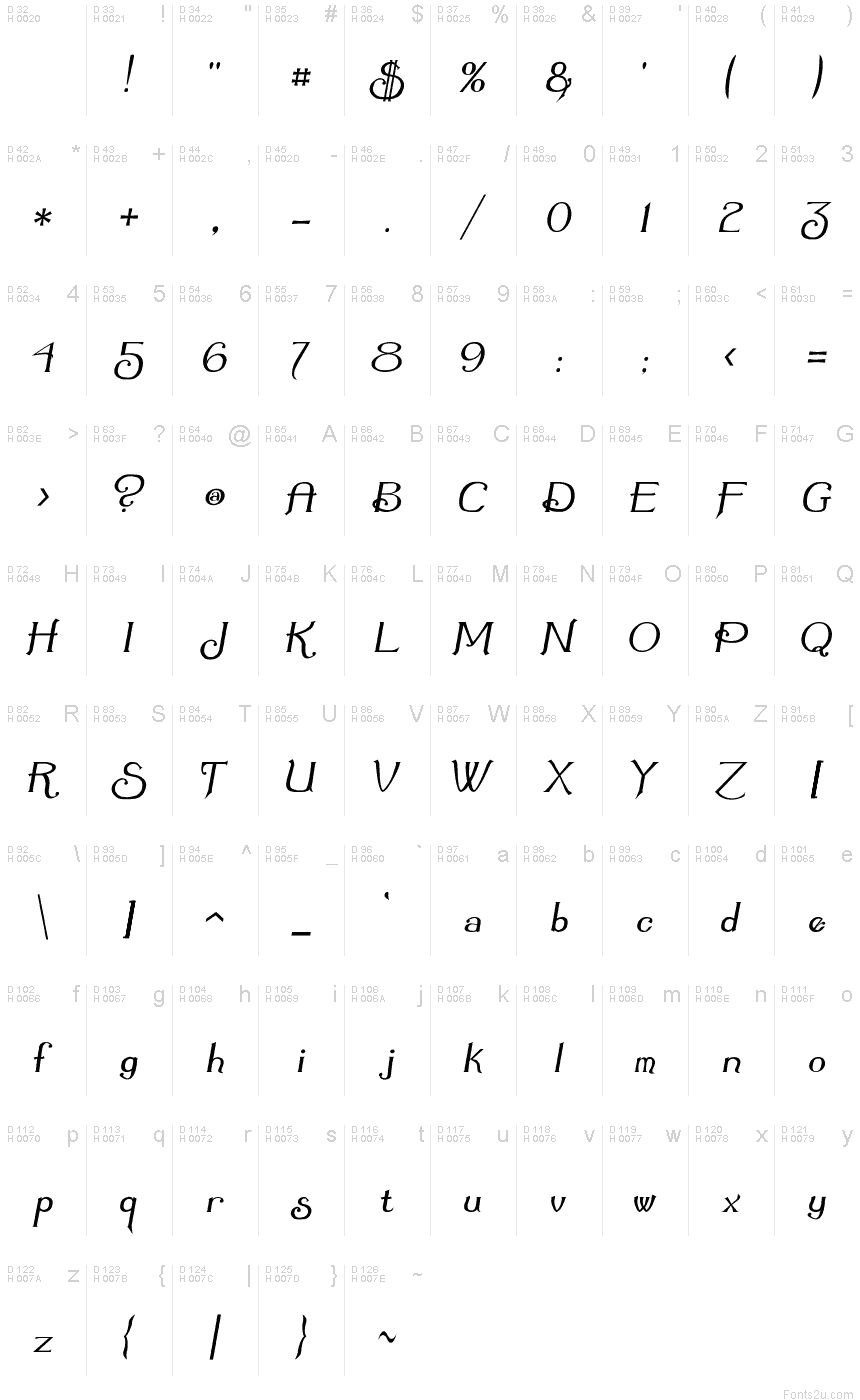
Summertime Oblique to darmowy krój kaligraficzny o lekkim, romantycznym nachyleniu. Litery sprawiają wrażenie zwiewnych i letnich, z szerokimi, zamaszystymi pociągnięciami, miękko zwężającymi się krzywiznami i kilkoma figlarnymi zawijasami, które nadają krojowi wdzięku, zamiast sztywności.
Naturalnie pasuje do zaproszeń, okładek książek, opakowań butikowych, menu kawiarnianych i krótkich nagłówków, gdzie odręczny styl potrzebuje odrobiny ogłady. Jako darmowy font, sprawdza się również doskonale w kartach tytułowych i monogramach, ponieważ długie kresy wejściowe i pętelki nadają nawet pojedynczym literom wystarczająco dużo dynamiki, by ożywić cały projekt.